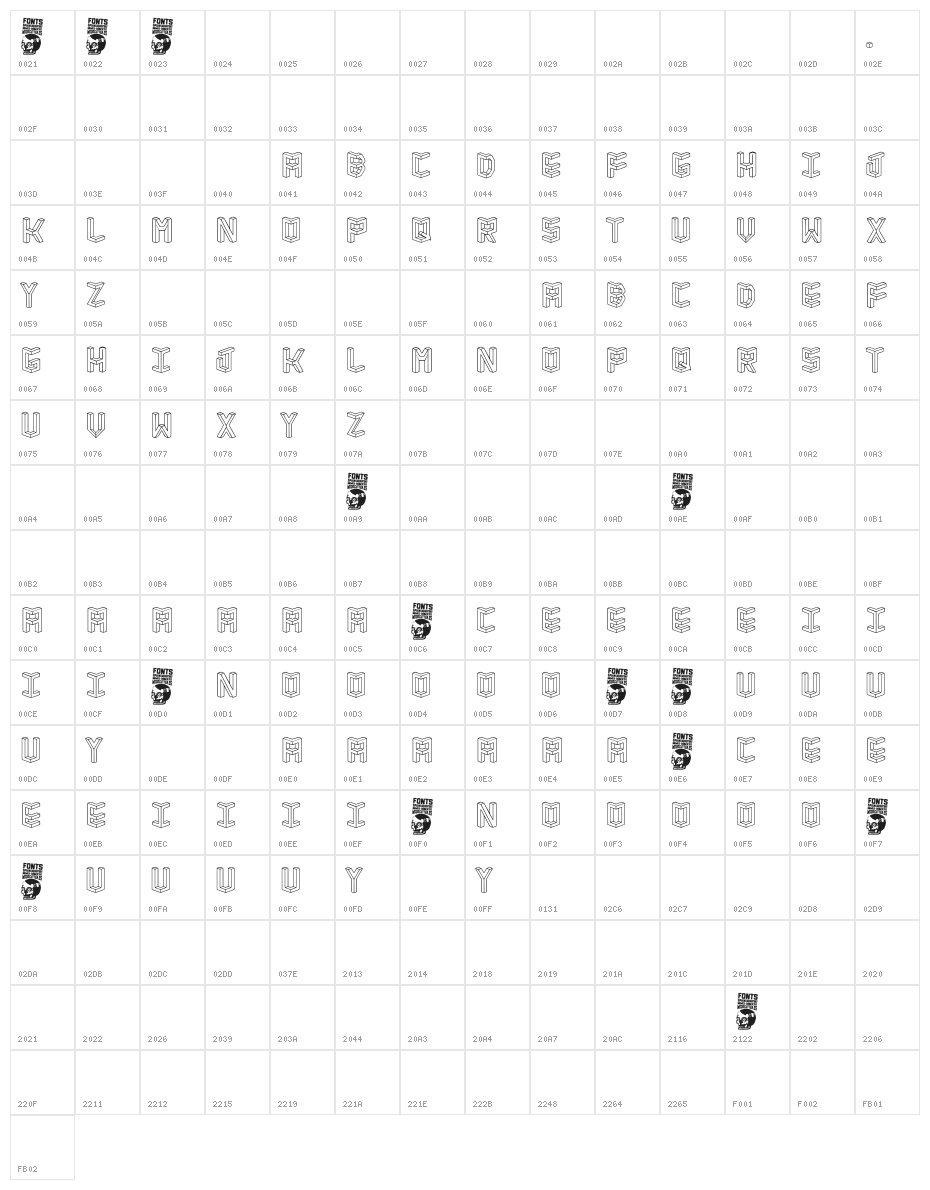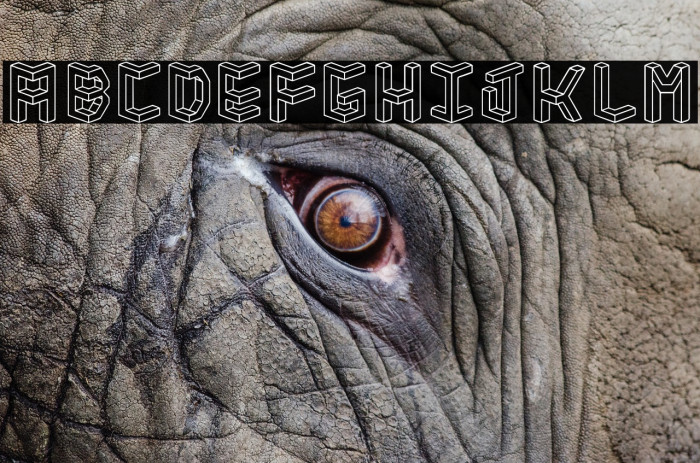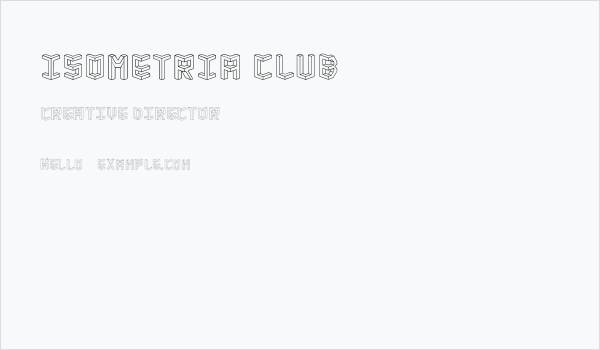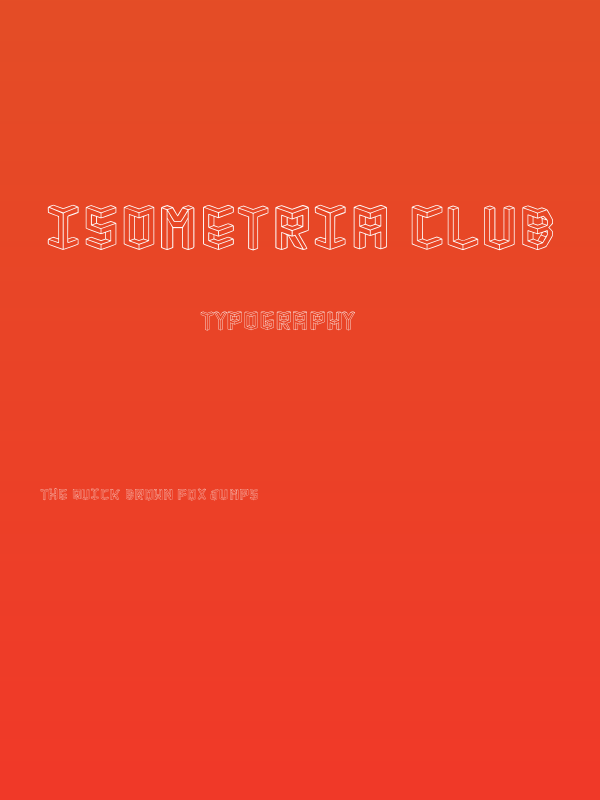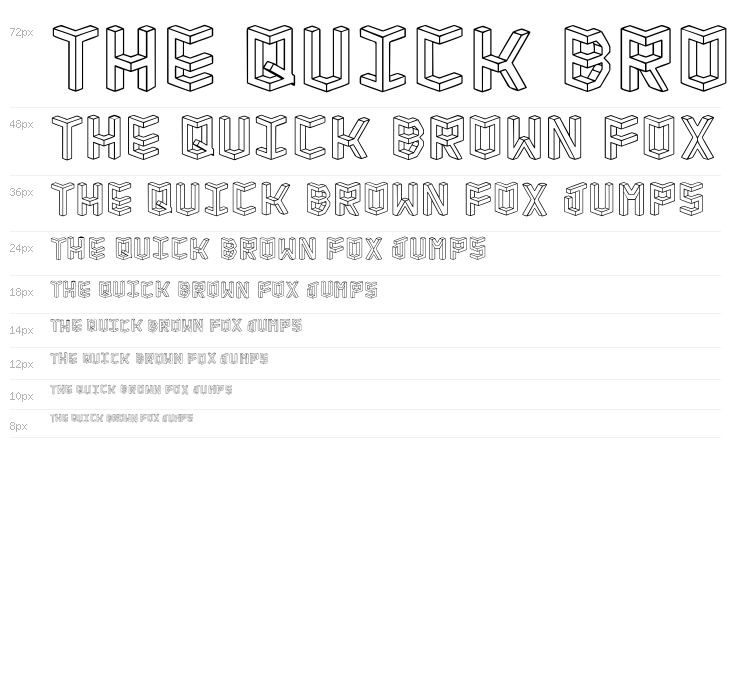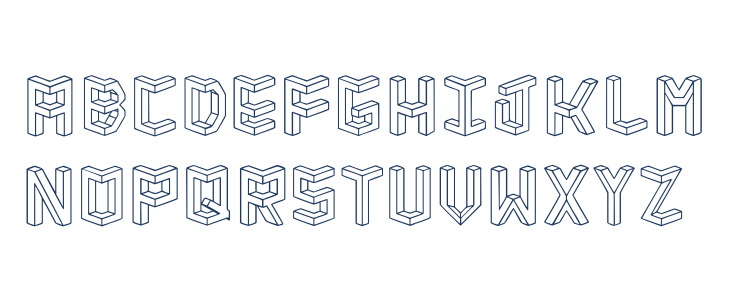
Isometria Club Font
| Nome | Isometria Club |
| Progetti proposti | Ideal for posters, logos, digital art, and any design needing a modern, eye-catching font. |